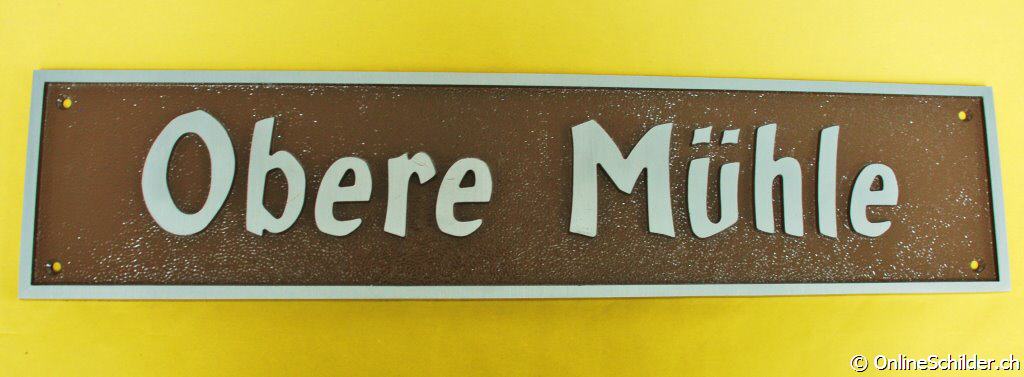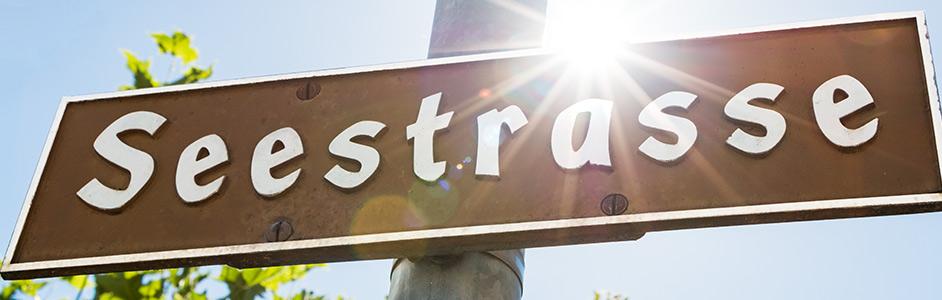
Strassenschilder Männedorf
Früher wurden Strassenschilder in Männedorf gegossen (siehe Bild). Heute wird bei Ersatz ein billiges Blechschild mit aufgeklebten Arial-Buchstaben verwendet. Dabei könnte man zumindest die gleiche Schrift wie früher verwenden, um optisch die Einheit zu wahren. Bei der Verwaltung kennt jedoch niemand den Namen der früher verwendeten Schrift. Erkennt jemand die Schrift auf dem Schild? Oder soll ich noch mehr Beispiele fotografieren gehen?
Das müssen nicht zwingend Buchstaben sein, die heute als Font erhältlich sind. Früher™ wurde das Design schon mal von der Gießerei erstellt, da sind dann Kriterien eingeflossen, die eine leichte und möglichst fehlerfreie technische Umsetzung sichergestellt haben.
Hier bekommt man ähnliche Schilder auf Bestellung, wobei die Form der Buchstaben ähnlich ist, die e allerdings im oberen Beispiel gedreht aussehen und das Gesamtergebnis eher fürchterlich aussieht. Aber vielleicht kann man in einem netten Gespräch Infos herauskitzeln …